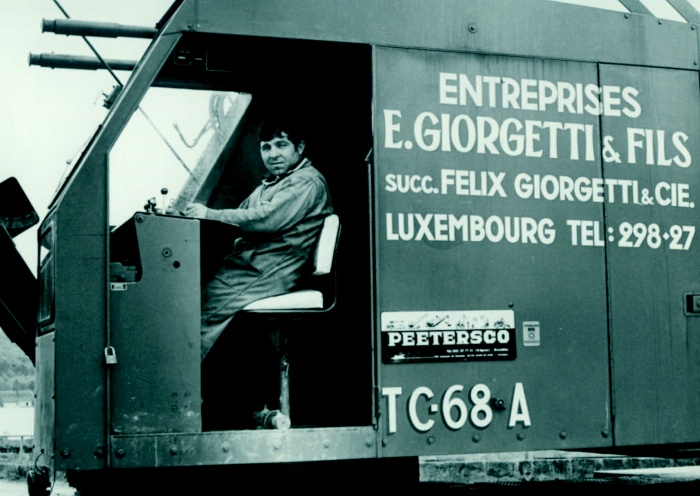
Schrift aus den 60'gern zu identifizieren
ich suche nach der Schrift, die auf einem alten Firmenwagen verwendet wurde. Ich habe ein Foto, das wahrscheinlich in den 40 gern, 50 gern aufgenommen wurde, und ich muss dieses Logo rekonstituieren.
Es geht mir um die Schrift aus "E.Giorgetti .... "
Es handelt sich um eine Luxemburger Firma, falls das hilft.
Ich habe schon alle Webseiten nach Schriften dieser Jahre abgesucht, aber nichts gefunden, das wirklich passt.
Ich glaub nicht, daß das eine Satzschrift war, sondern eher, daß es sich um die Kreation eines Schildermalers handelt. Du wirst also im günstigsten Fall maximal etwas Ähnliches finden ...
Die Serifen/Spitzen von T und E haben so ein bisschen was von Albertus
Der Rest ist aber wesentlich schmaler.
Vielleicht findest du unter dem Suchbegriff Flareserif etwas, was du als Ausgangsform benutzen kannst.
Clearface Gothic geht auch in die Richtung ...
Auch ich gehe davon aus dass diese Schrift das Kunstwerk eines Schildermalers oder gutem Fahrzeug-Lackierers war. Dies wurde ja damals mittels Bleifolie direkt auf der zu beschriftenden Fläche geschnitten, nachdem die Skizze, die ebenfalls von Schildermaler selbst gezeichnet wurde mit einem Kopierrad auf die Bleifolie übertragen wurde. Als ich in den 1970ern in der Lehre war, wurde diese Technik bei KFZ-Lackierern noch gelehrt.
Damals gab es als großformatige Holzlettern auch nur recht wenige Schriften, das Gros der Plakatschriften, Werbeschildern und Fahrzeugbeschriftungen wurde frei gestaltet. Leider sind auch von den alten Holzlettern-Plakatschriften viele achtlos ins Feuerholz gegangen, als neue Techniken die Verwendung von Satzschriften (die freilich oft nicht für derart große Schriftgrößen entworfen wurden) ermöglichte.
mal abgesehen davon, dass sie in die falsche Richtung zeigen ...
Im Bleisatz hat man solche Schriften als serifenlose Antiqua (Varia) bezeichnet, heute fällt sowas unter das weite Feld Retro, darin auch gern oft falsch als Art Deco oder noch falscher als Jugendstil bezeichnet. Mir scheint die Schrift eher französischen Traditionen von Schildermalerei zu entstammen, die Grotesk sieht mir auch eher französisch/italienisch als deutsch oder holländisch oder englisch aus ...
Falls Dir das Buch Retrofonts (Schmidtverlag, mit CD)  irgendwie zugänglich sein sollte, darin könntest Du eventuell eher was in die Richtung finden.
Dies wurde ja damals mittels Bleifolie direkt auf der zu beschriftenden Fläche geschnitten, nachdem die Skizze, die ebenfalls von Schildermaler selbst gezeichnet wurde mit einem Kopierrad auf die Bleifolie übertragen wurde. Als ich in den 1970ern in der Lehre war, wurde diese Technik bei KFZ-Lackierern noch gelehrt.
Vielleicht kannst Du ja bei Gelegenheit diese Technik hier mal in allen Zwischenschritten beschreiben. Ich bin trotz des Bildes noch nicht so recht schlau geworden, wie genau das funktioniert hat.